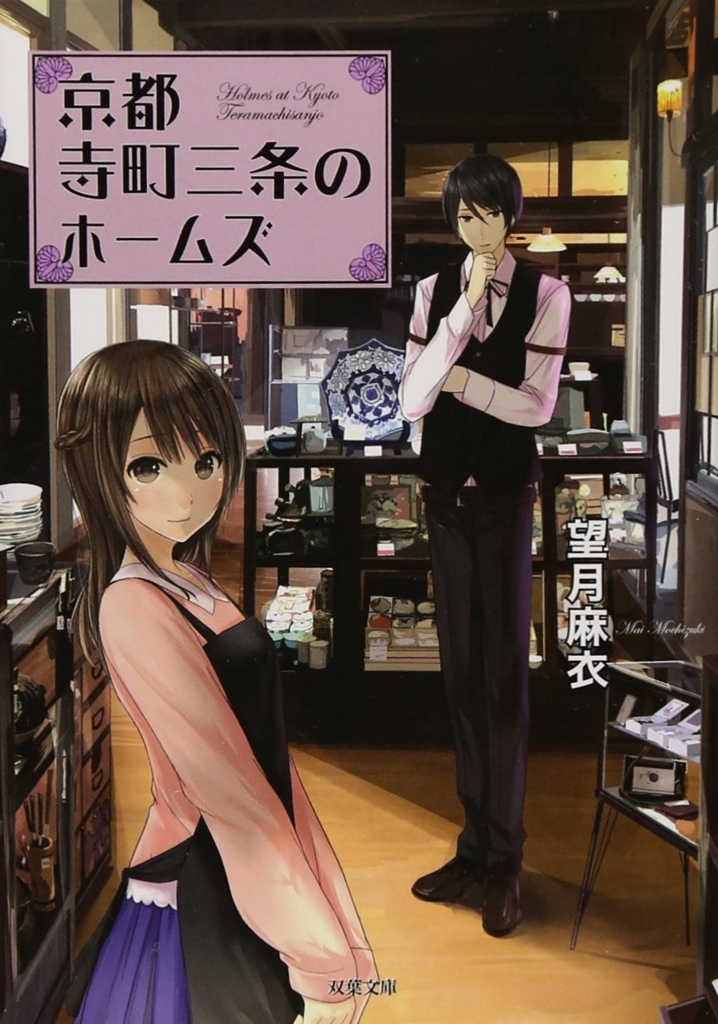
京都寺町三条のホームズ
「京都寺町三条のホームズ」は、望月麻衣氏著書によるミステリ小説シリーズ。
望月麻衣Profile●北海道出身。2013年にエブリスタ主催第二回電子書籍大賞でデビュー。2016年『京都寺町三条のホームズ』が『京都本大賞』を受賞。
京都寺町三条のホームズシリーズのタイトルのフォントにロマン雪が採用
双葉文庫「京都寺町三条のホームズ」シリーズのタイトルにダイナフォントのロマン雪が採用されている。
ロマン雪
1925年の藤原太一著書による『図案化せる実用文字』からインスパイアされ、図中の婦人の華麗な装いや愛らしいスタイルをヒントに大正末期から昭和初期にかけての古典ロマンの雰囲気を再現した書体。ひし形など独特の字形が大きなインパクトを与える事から、ロゴやPOPなどで大きく活用できる。